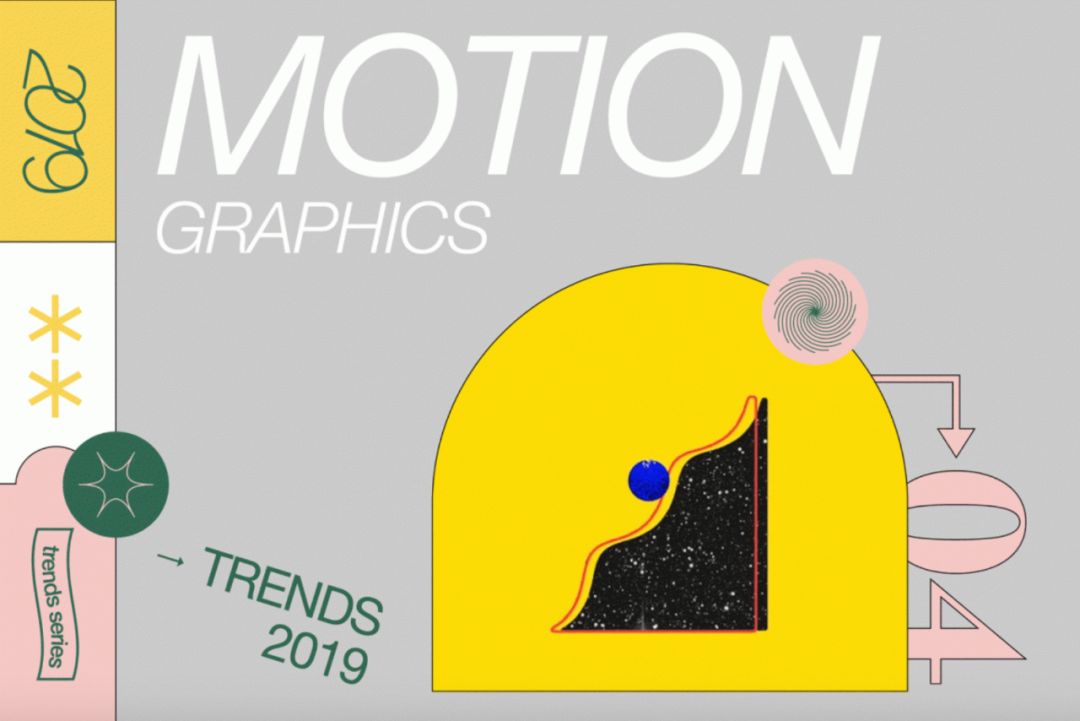
10个 Motion Graphics 未来趋势,我们该怎么用?
如果你需要将一个复杂的概念简化,但是又不知道用什么方式?
那答案肯定是:Motion Graphics(动态视觉)。它是视觉性与叙事性的完美结合。不仅能让视觉引人入胜,而且还可以帮助品牌清晰快速地分享他们的故事。
2019年,Motion Graphics 已然是设计群体热爱并热衷于创作的方向,还没有接触的同学也不要担心。本次推送,是来自 WIX.com 的 2019 Motion Graphics 趋势。不如先看看喜欢哪种风格,再开始也不晚。
01
#动态排版
Kinetic Typograhy
作为设计师,我们需要遵守一定的规则。素材图片是一个很大的禁忌,没有按住“Shift”键的情况下去调整图像大小给我们带来了不少痛苦。文本也是如此 - 我们被教导永远不去拉伸或扭曲字母。事实上,有时候规则是会被打破的,就像现在使用动图的排版世界。我们可以看到越来越多设计师在推动动画排版的界限 - 在所有方向上拉伸,扭曲,像素化和变形文本,将常规字母“脱颖而出”,塑造出近乎3D的结构。
《A-Trak》 是这种运动图形趋势的完美示范,探索了简单无衬线字体的可能性。
《Basketball Forever》整套视觉语言围绕着这两个词的本质,“篮球”和“永远”,以体现运动的主题,围绕着文字动画的方式呈现出了运动的连续性和速度感。
02
#破碎的文字
Broken Text
破碎的文字是排版另一个重要主题,虽然不是新趋势,但我们可以看到它的新用途将其带到另一个境界。文字四处“游荡”,一个个逐渐出现在不同层级,在屏幕中分散,或者被解构。
在知名主厨 Francis Mallmann 关于“成长”的引述短片中,令人感伤的台词伴随着旁白的声音出现,动画以诗的形式,视觉再现了台词表达的意思。
被拆分成一个个“选项”的“choices”;
会“升高”的“Growing Up”。
由 Enle Li 和 Liz Xiong 共同创作的《Words》,更是将文字与文字本身的含义进行完美结合。告诉你,破碎的文字可以...
模拟交通  🚗
行人 🚶
或者是一场气候变化:☀️🌦🌧️⛈
03
#无缝过渡
Seamless transitions
无缝过渡是这些趋势中,最能走进内心的,这也是其这么多年来一直很强势的原因,过渡已经成为一个主要的主题。设计师正在使这种“顺滑”的技术实现得更具现代感。场景之间缺少停顿,相互融合的特点使视频具有非常流畅的感觉。
在 Le Cube 的《The Confidante》中,场景无缝地转变为新的画面。文字在视频中充当着引人注目的角色,能引起观众对图像的关注,而其他元素在背景中发生着变化,从模糊、不明确的斑点和形状变为人物和物体。
相似的效果可以在 Pablo Lozano 为 Tamara Qaddoumi 制作的MV中看到。这段情感化的视频带我们踏上旅程,流动的抽象形状有助于在场景之间形成平滑的过渡。
04
#细线条
Thin lines
线条肯定被低估了。尽管它们很简单,但在设计中具有无穷无尽的功能,从暗示方向,定义形状,分隔不同元素等等。当有机会移动和“跳舞”时,简陋线条的可能性将变得无穷无尽。我们现在可以看到,线条在动态设计中的使用率越来越高,它们融为一体,被设置成动画,以创造各种效果。
由 Clement Virgo 执导的《The Canadian Experiment》中,线条起到了突出作用,它们被用作形状的轮廓,以及形成动画人物衣服上的图案和装饰。在某一点上,线条本身成为了焦点 - 只保留了形状的轮廓,没有填充颜色,创造出一种矢量标志的感觉。
《Build Connections》中,线被使用得更加自由。几乎像是在现场绘制,动画看起来好像一只真手在勾勒图表,箭头或其他元素,宛如置身于别人的笔记本里。线条在屏幕中飞舞,增长,缩小,巧妙地转换成文本或其他视觉元素,营造出俏皮的氛围。
05
#颗粒感
Grain
干净,简单实用的几何形状可以很棒,就像清爽的白色办公空间或日本美学的精致简约。但有时候,我们想让它活跃起来。这就是“颗粒”的用武之地——一种用于动态设计的工具,为视觉效果增添了一种“噪音感”,否则这些视觉效果会显得平淡而毫无生气。其实这种动态视觉趋势也被运用在插画中,因为它能巧妙又强有力地为基本矢量图像添加纹理,使视觉效果更加贴合。
在 Allen Laseter 这则视频中 ,“颗粒感”绝对是整段影片的加分项,视频受启发于一位喝醉的顾客发给 Lagunitas 公司的语音留言,浑厚、粗旷的男音与“颗粒感”相辅相成,呈现出更加完整的粗糙感。
YouTube 的 Space Valley 频道一个令人愉快的视频中,纹理的使用将原本简单的2D形状转换得更具纹理和厚度。它还赋予了复古的氛围,真正赞美了怀旧的动画风格。
06
#液体动态
Liquid motion
和用于放松内容贫乏的几何、矢量图像的颗粒感相同,液体动态也为动态影像设计增添了有机感。这类趋势并非干净利落的过渡和移动,取而代之的是颜料的飞溅,在屏幕中像液体一样流动和舞动,转变成新的形状,并在沿途中创造一些真正的视觉享受。
在 Upwork 的视频中,液体动态用于传达运动感和戏剧感; 一个场景飞入另一个场景,这种惯性最终导致火箭起飞,抽象的形状继而变成它的踪迹。
Buck 为 Facebook 的国际妇女节制作的视频也运用了液体动态,颜料像五彩纸屑一样在屏幕上极速穿过,从而产生出一种庆祝感。通过使用液体动态,创造了具有吸引力的手工的感觉,使主体更加平易近人,观众对此更有亲切感。
07
#2D和3D的结合
Liquid motion
Nostalgia 是一个强大的设计工具。我们都喜欢回想孩提时代的经典2D动画,现在的科技能使我们实现得更多,设计师们开始将这种复古的2D风格与当代的3D动态影像技术相结合。这些类型的动画一开始会显得平坦,甚至像纸一样,但通过把相机不同角度的移动进行整合,为不同元素增加立体感和深度。
这部动画电影《Away》的预告片具有熟悉,怀旧的2D质感。但逐渐地,你会注意到相机镜头似乎在拉近和转化,使场景变得生动。
Motion Corpse 的这部动画乍看之下像是一幅拼贴画,但也保留了令人惊讶的3D旋转。
08
#醒目、大胆的排版
Big, bold typography
设计文本世界另一个主要趋势是大型的,醒目排版。我们还可以看到这种趋势被许多网站使用,因为它让品牌和设计师有机会清晰地传达他们的信息,大胆地展示他们是谁以及他们代表什么。
这个为 G-Dragon 的 MV 制作的视频强调了该类型。歌词在整体的信息中起着至关重要的作用,设计师 Le.Ho.An 为这些文字提供了应得的平台,占据屏幕的文字构成了视频的主视觉。
State 的视频《Understated》质疑人们普遍认为的观念——我们应该找到自己的个人风格并努力完善它。相反,他们认为生活的重点更多是“创造酷炫的东西。”为了强调这一点,视频通过对技术和流行趋势进行美妙的错配,用巨大的屏幕标志作为不同风格和场景之间的过渡。这件作品将带你踏上从超现实的3D视觉效果到粒状插图,再回到复古色调的旅程。
09
#等距设计
Isometric design
在二维屏幕上表现三维空间和物体已被证明是过去几年中备受关注,讨论和引起动荡的中心。我们一直在寻找表现物理活动和物体的最佳方式,例如我们设计和开发越来越多移动app中的笔记本电脑或麦克风。曾经风靡一时的拟真设计(Skeuomorphism),现已被平面设计所取代。等距设计已经与其他风格挤在一起,试图找到一种在屏幕上表现3D元素的方法。
Pikotea 应用程序的各种功能可以在以下视频的等距世界中看到,创造出了适用应用程序功能的数字化和嬉戏的氛围。
具有等距,高分辨率风格的高度数字化虚拟世界也在 JVG 的《Guerlain:Météorites》中得以传达。艺术总监 Peter Tarka 的视觉语言在影片中被放进一个旋转的3D循环中。
10
#数字化超现实主义
Digital-surrealism
继续探索设计师如何在平面屏幕上呈现真实的三维生活,一种新的趋势开始出现:数字-超现实主义。这种风格描绘了一个超现实的虚拟世界,由高度清晰的视觉效果和材料组成。材料和数字设计的交集实现了在现实生活中不可能出现的行为:从永不爆开的气泡到蒸发成稀薄空气的物体或无视重力和液体神奇地转化为固体。
下面的动态影像设计宣传视频是由数字艺术家 Daniel Aristizábal 为三星新推出的相机而制作的,延伸了材料的极限,创造出熟悉物体的迷人意象,表现出它们与现实生活相悖的行为。
Moth Studio 为电视频道 E4 创作的视频也是如此,将3D的字母与类似自然的高度数字化视觉效果融合在一起。